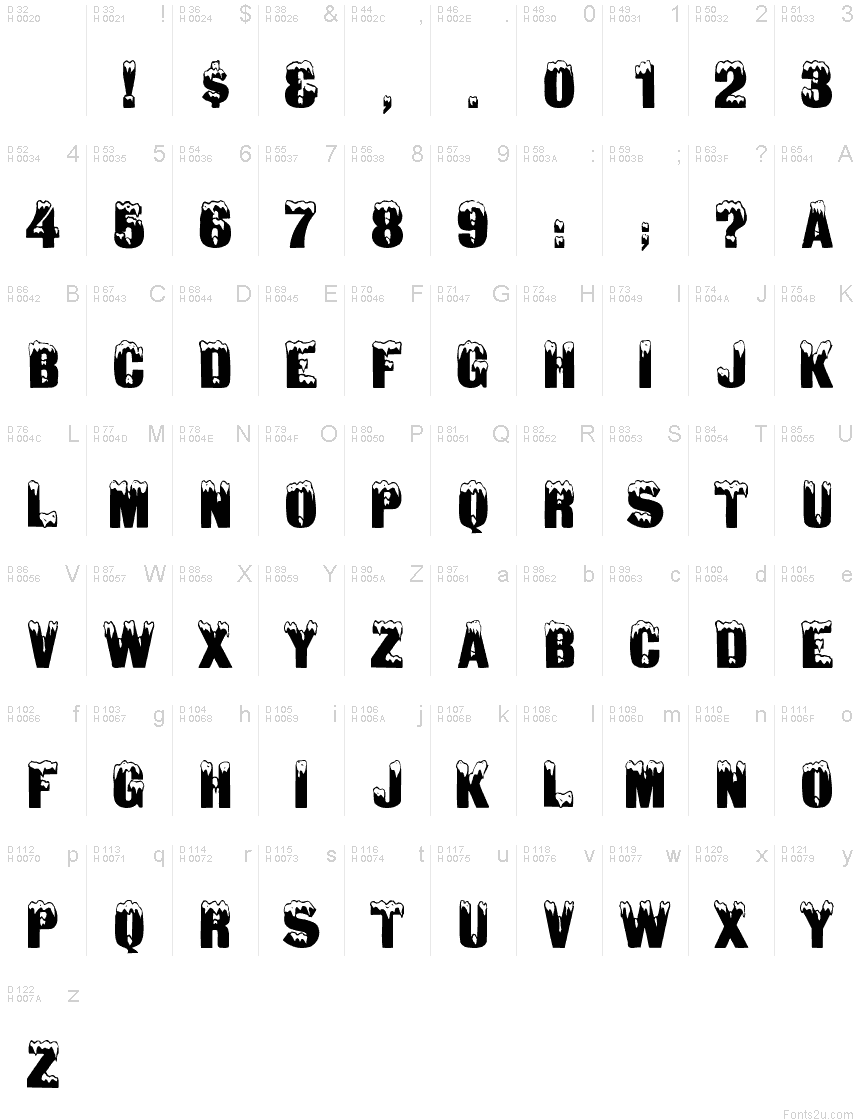
Igloo Caps è un font display gratuito in stile cartoon che trasforma ogni parola in un titolo innevato. Le lettere spesse e squadrate sono ricoperte da uno strato di ghiaccio che cola sui lati, come neve fresca accumulata su un tetto. Le forme nere audaci e la «brina» bianca brillante creano un look invernale d'impatto, ben leggibile anche da lontano, mantenendo uno spirito amichevole e giocoso.
Con Igloo Caps, i tuoi progetti invernali avranno subito un tema perfetto, senza bisogno di illustrazioni extra. Questo font gratuito è ideale per locandine natalizie, schede didattiche per bambini, titoli di giochi, inviti, miniature di YouTube e adesivi stagionali. Usalo in grande per il massimo effetto e abbinalo a un semplice font sans serif arrotondato per il testo principale, così da lasciare che siano le lettere ghiacciate a rubare la scena.
IglooCaps